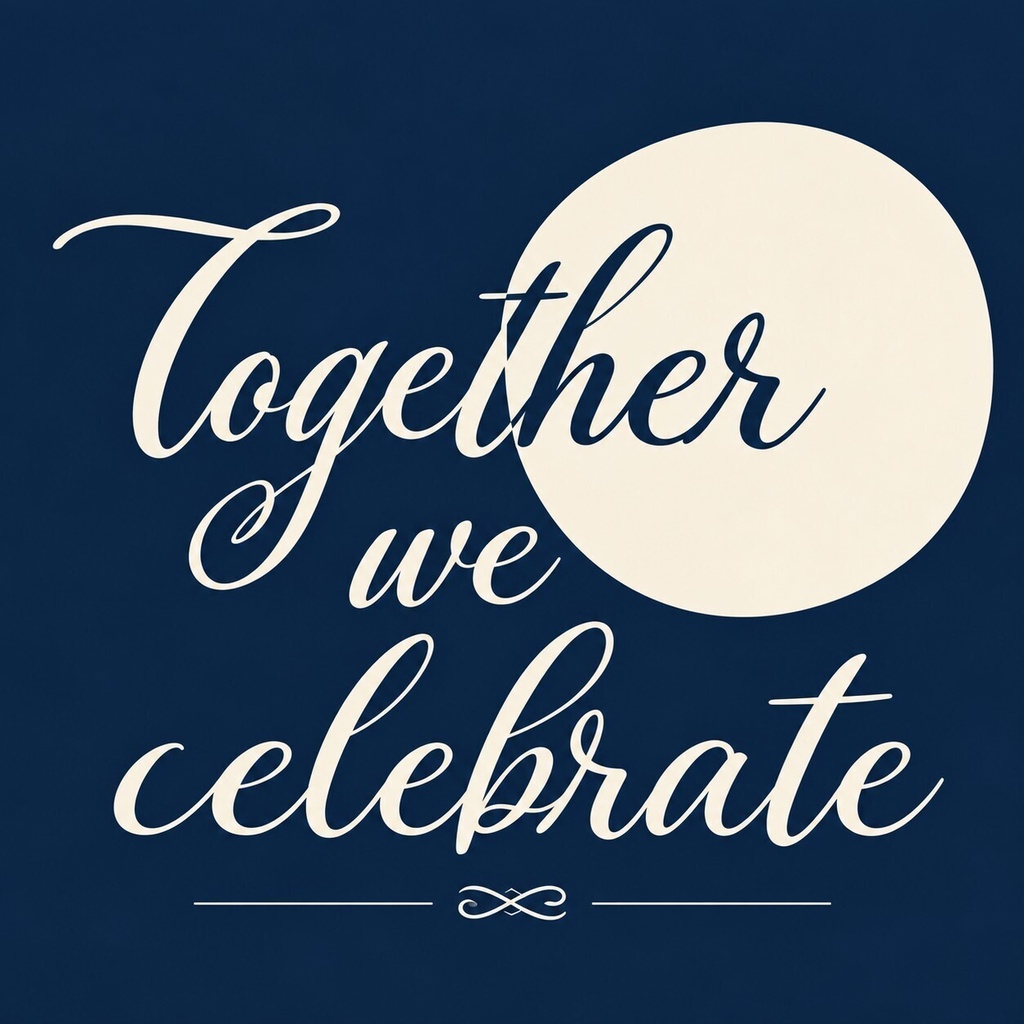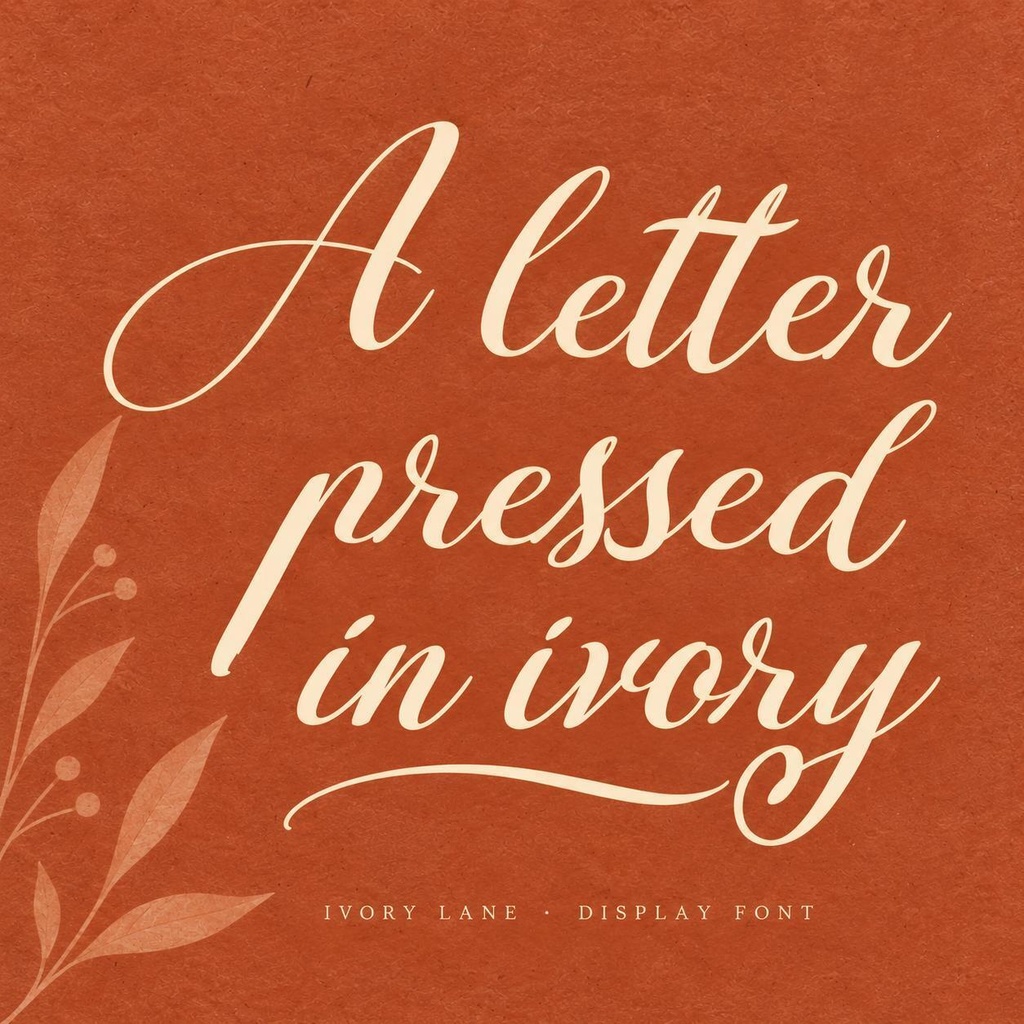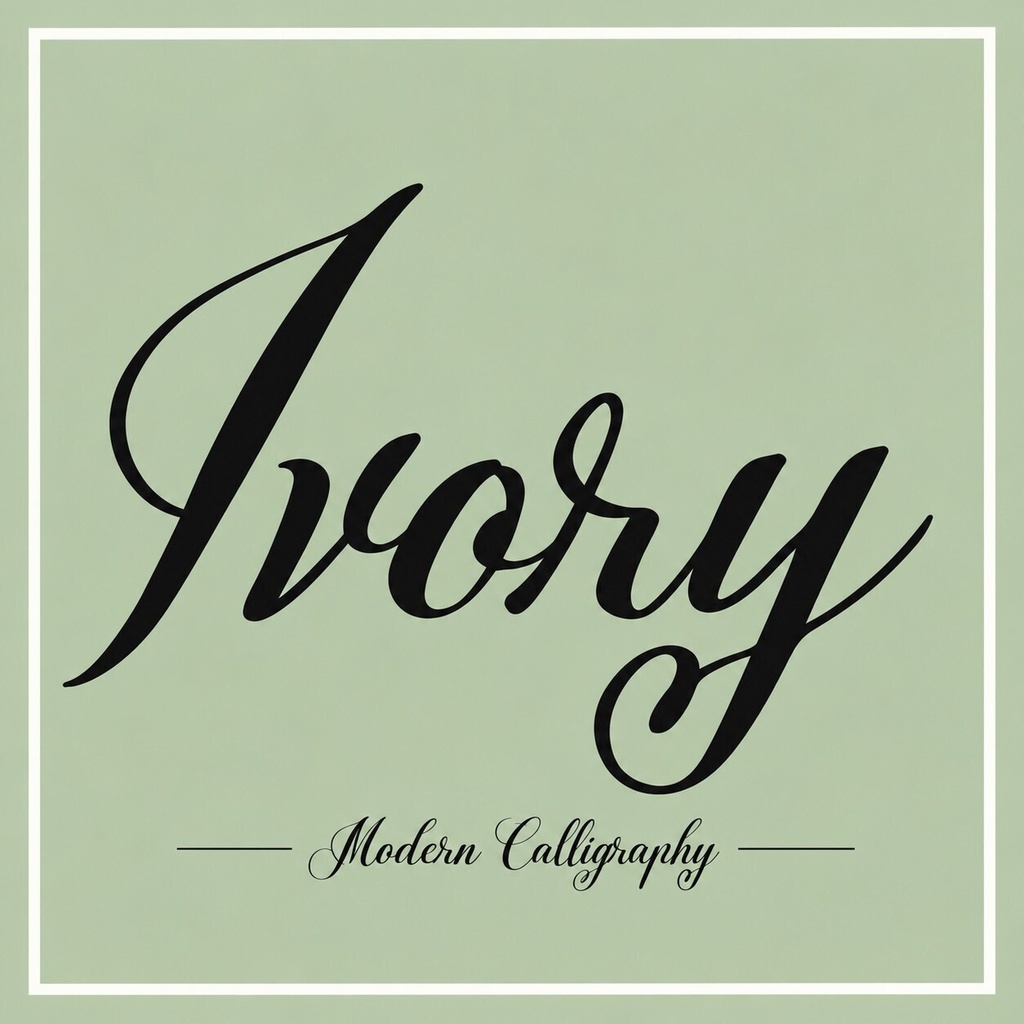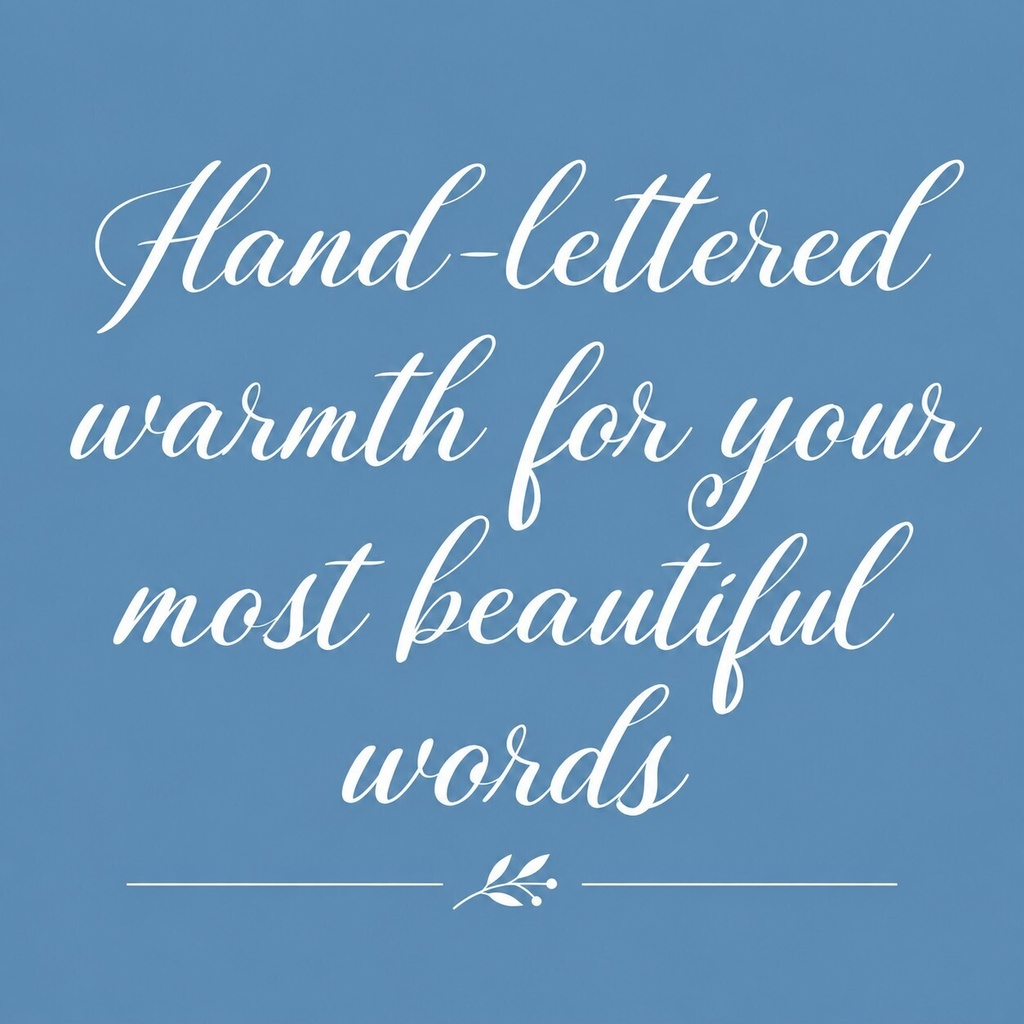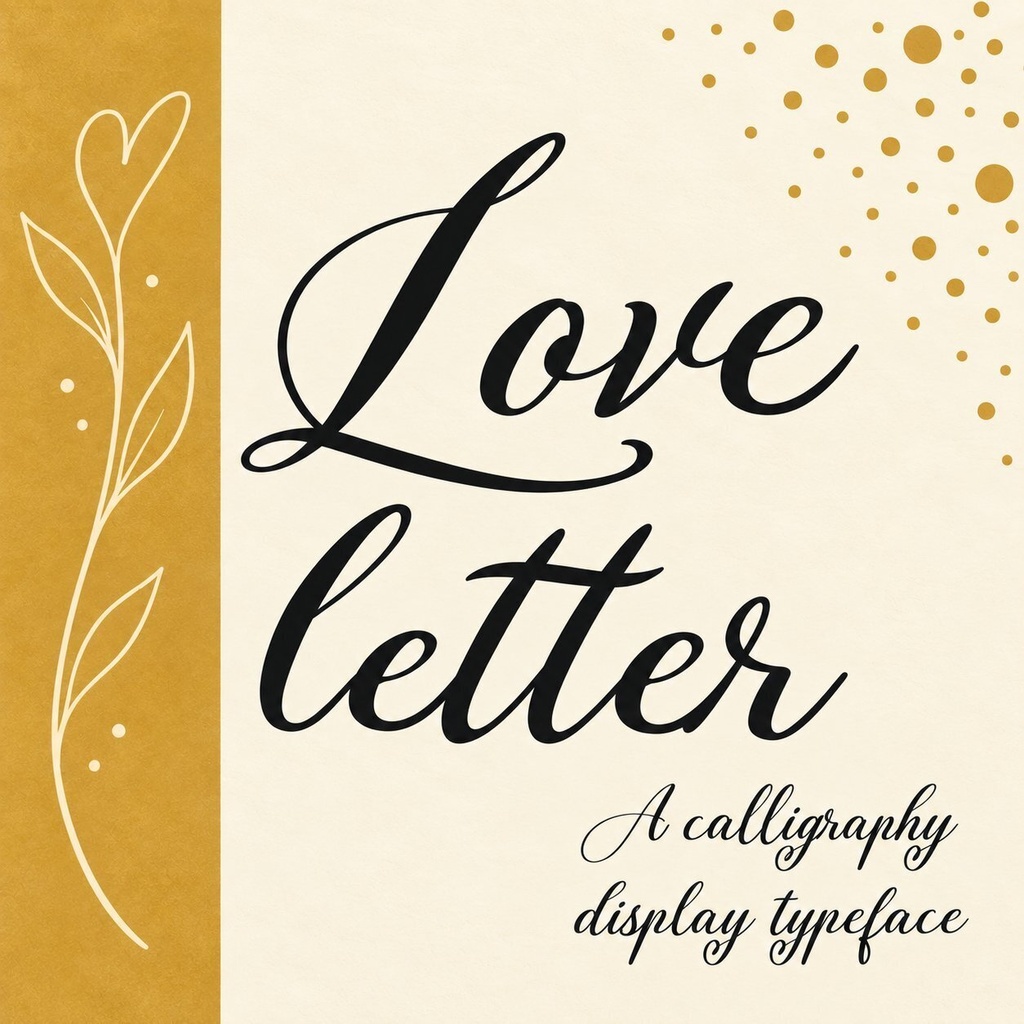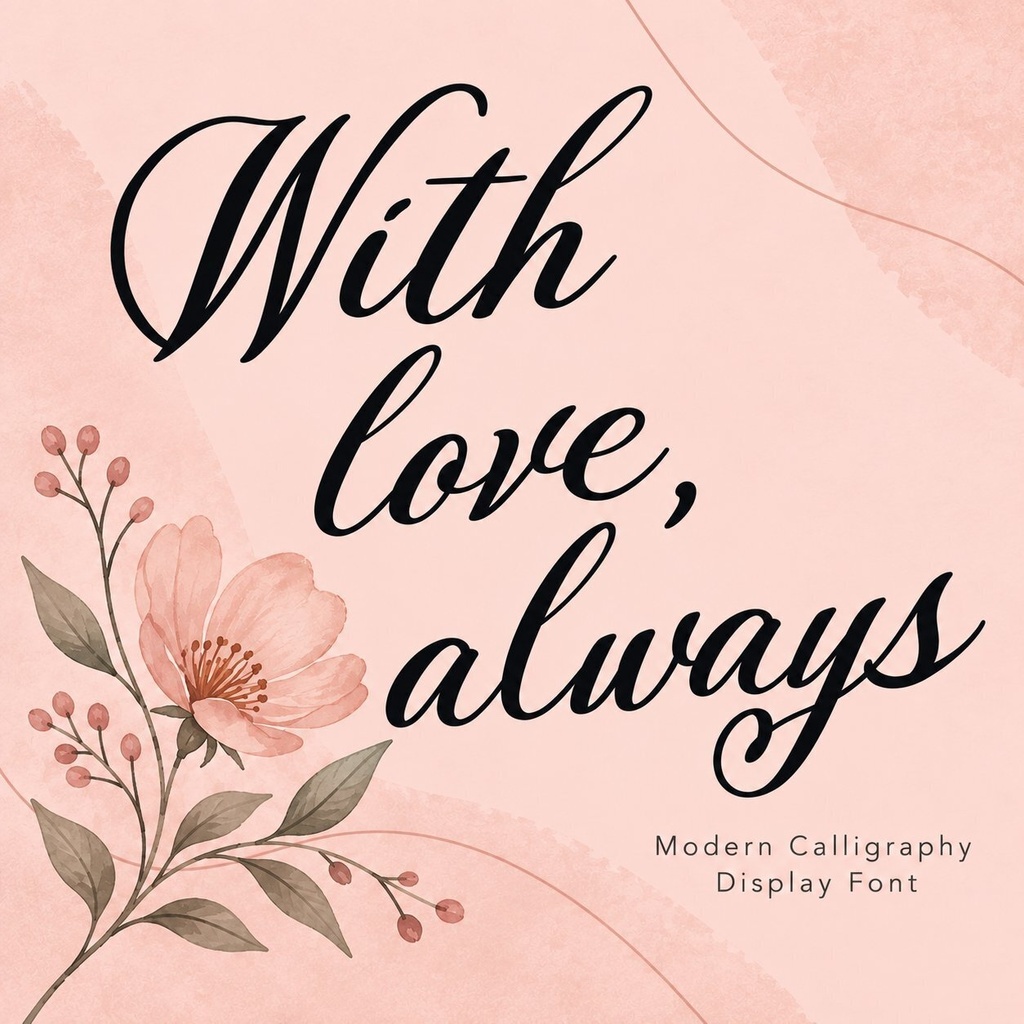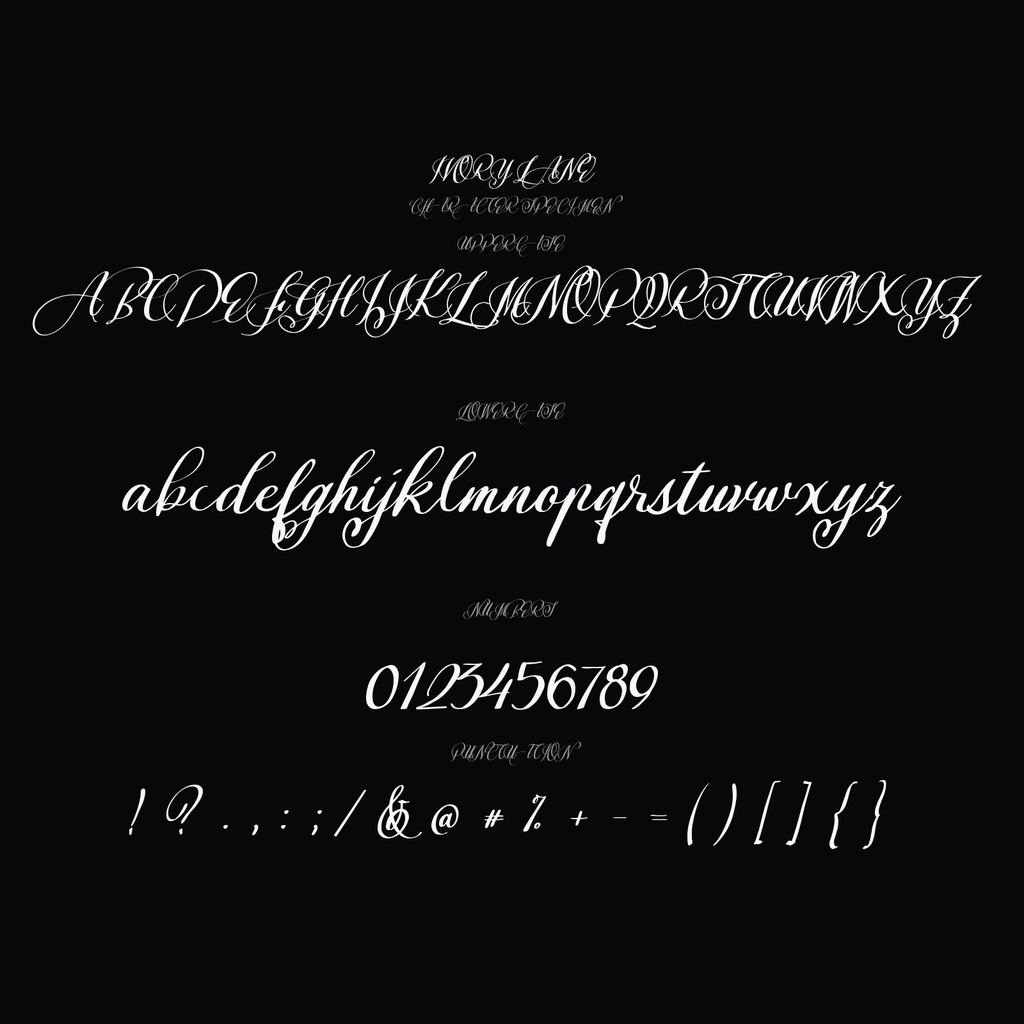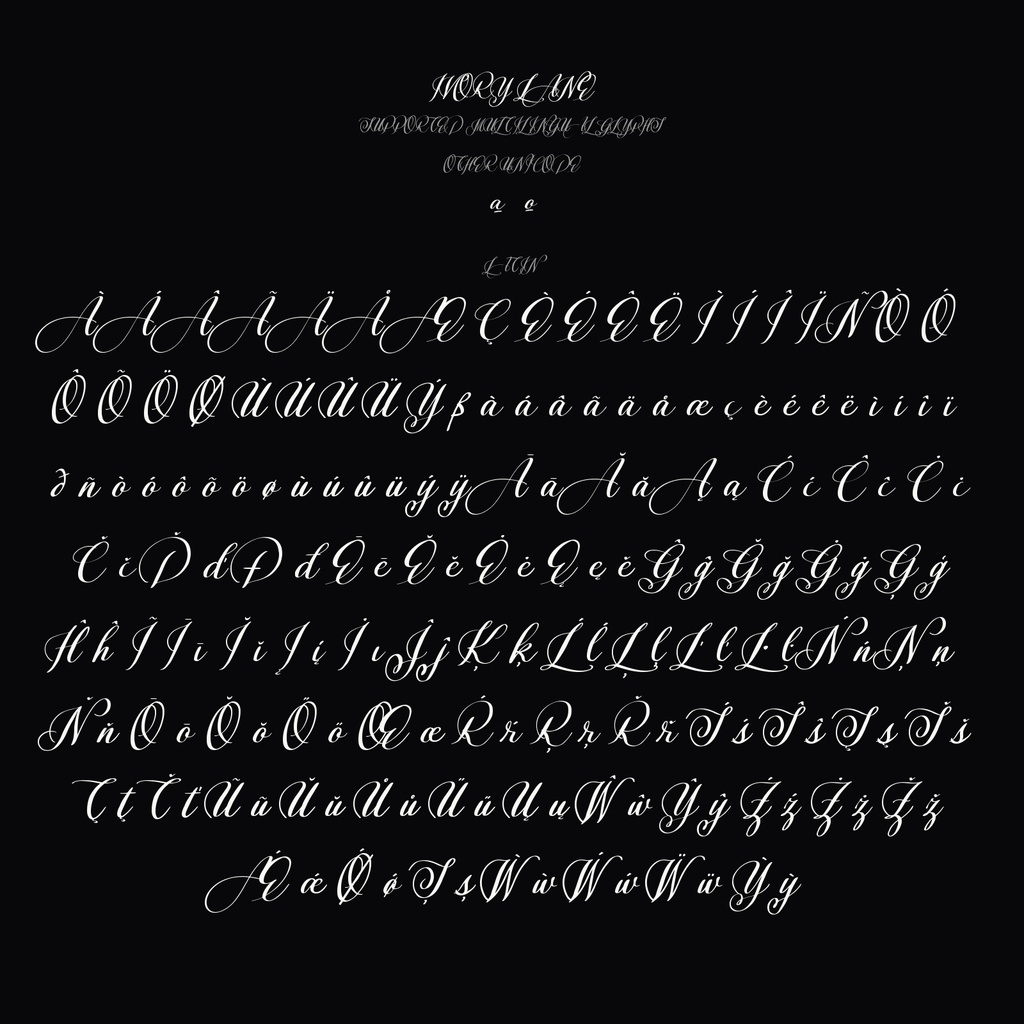
Ivory Lane(アイボリー・レーン)【カリグラフィフォント】
ウェディング invitation やロゴデザインに映える、モダンなカリグラフィフォントです。やわらかな筆致と不規則なベースラインが、トレンド感あふれるフェミニンな雰囲気を生み出します。 Ivory Lane は、装飾的なキャラクターと有機的な揺らぎを持つモダンカリグラフィ書体です。ウエディング invitation、グリーティングカード、ロゴ、ビジネスカード、SNS グラフィックなど、洗練されたデザイン制作に最適です。 ## 収録内容 - フォントファイル一式(OTF, TTF, WOFF, WOFF2) - 全角・半角英数字、記号、装飾キャラクター - リガチャー・オルタネイト対応(GSUB) ## 対応文字 - 英語アルファベット(A-Z, a-z) - 数字(0-9) - 記号・装飾文字 - 多言語対応(包括的なキャラクセット) ## 用途 - ウエディング invitation・セーブ・ザ・デート・カード - グリーティングカード・サンクス・ユー・カード - ロゴデザイン・ブランディング - ビジネスカード・ステーショナリー - イベントプログラム・メニュー - SNS グラフィック・クォート画像 - フォトグラフィーウォーターマーク ## 形式 - OTF(OpenType Font) - TTF(TrueType Font) - WOFF(Web Open Font Format) - WOFF2(Web Open Font Format 2) ## 対応環境 - macOS / Windows / Linux - Adobe Photoshop / Illustrator / InDesign - Figma / Sketch / Canva - 主要なグラフィックソフトウェア ## 利用許諾 本フォントは FontFairy 商用フォントライセンスの下で提供されます。商用利用可能(商用可)。利用条件の詳細は付属のライセンスファイルをご確認ください。